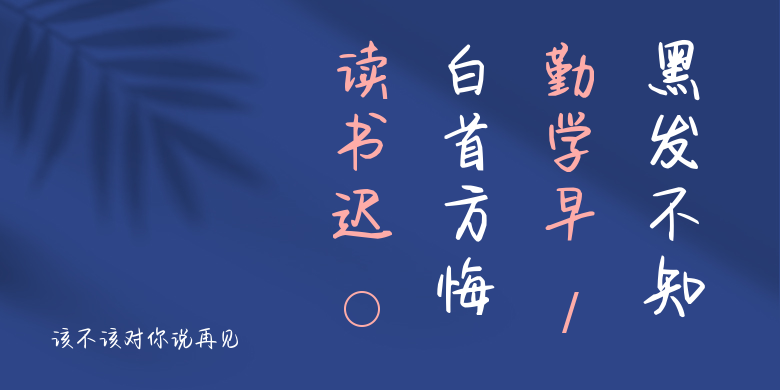
该不该对你说再见
该不该对你说再见,这款字体结构工整、笔画清晰,兼顾美观与易读性,适用于标题、正文、海报、包装、LOGO 等多种场景。字形优雅稳定,风格百搭耐看,适配日常排版与创意设计,让文字呈现更舒适、更具质感。该不该对你说再见一笔一画,皆是细节,以均衡的比例、流畅的线条打造舒适视觉体验,字形端正大气,风格简约现代。无论是商业设计、品牌宣传还是日常排版,都能轻松驾驭,让文字更有格调与力量。该不该对你说再见字体下载。